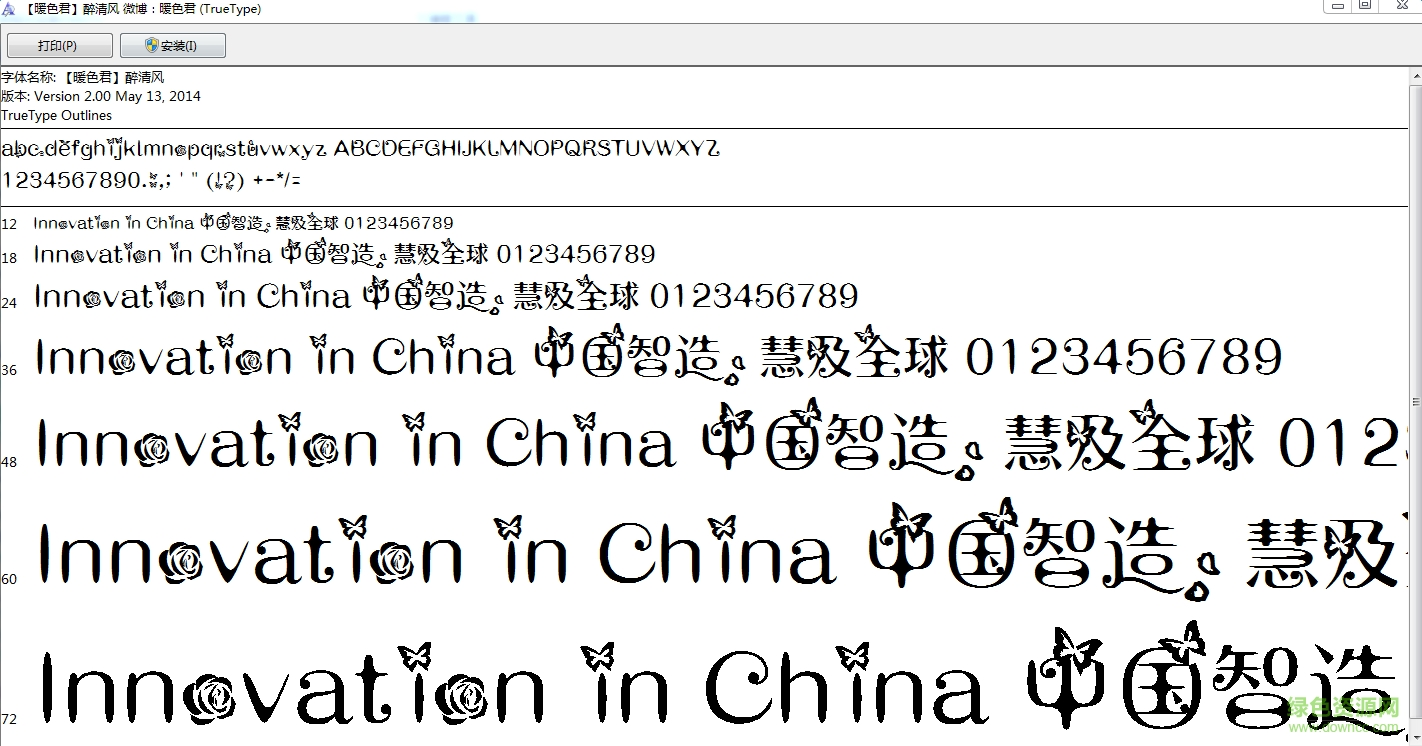
蝶醉清風(fēng)字體是一款非?;ㄇ蔚?a href="http://m.lz0519.com/k/yishuziti/" target="_blank">藝術(shù)字體,字體圓潤(rùn),筆畫帶勾,字形中融入了特別的蝴蝶和玫瑰花元素,文案更加生動(dòng)有趣,喜歡的小伙趕緊來綠色資源網(wǎng)下載收藏吧!
蝶醉清風(fēng)字體是一款用于花紋設(shè)計(jì)方面的字體,字形唯美哥特,喜歡的朋友就下載看看吧,相信你會(huì)喜歡上這款非主流個(gè)性字體的。